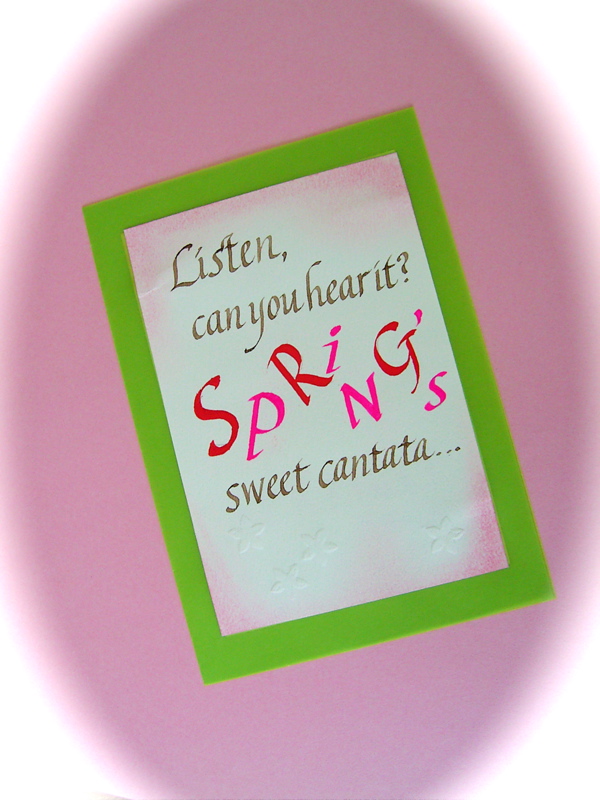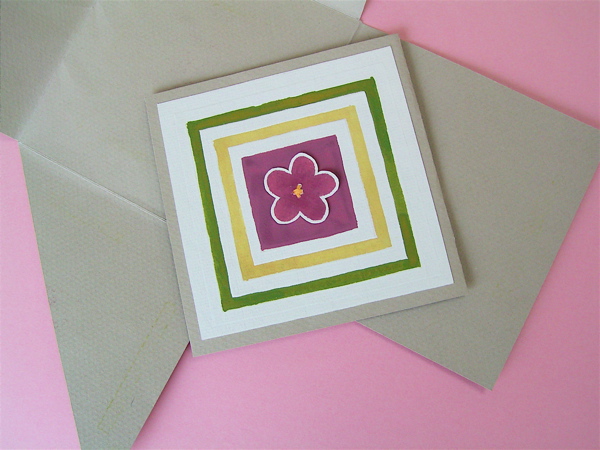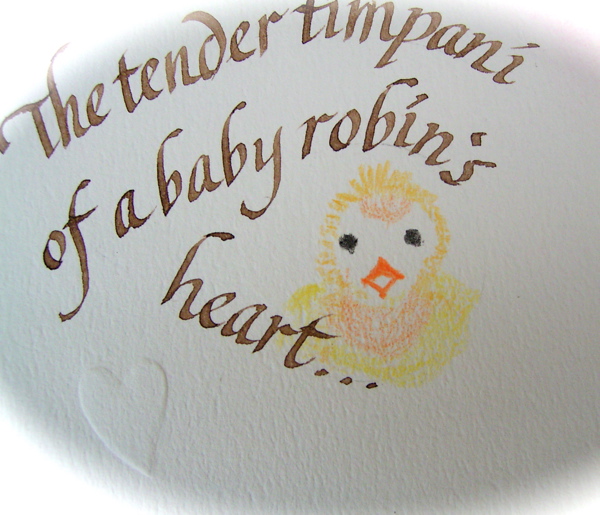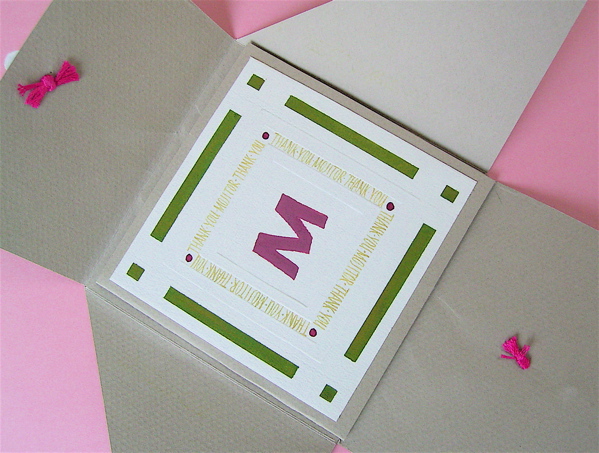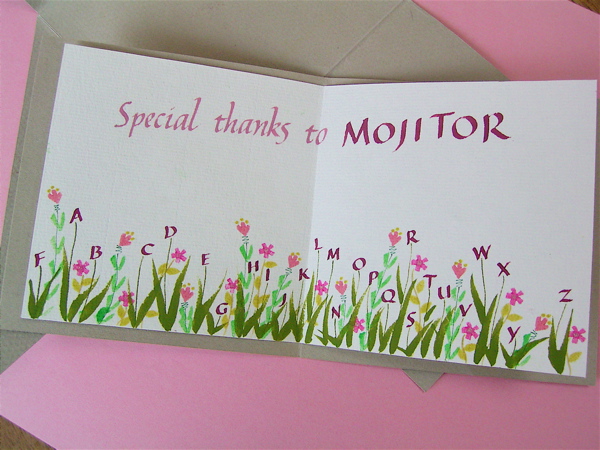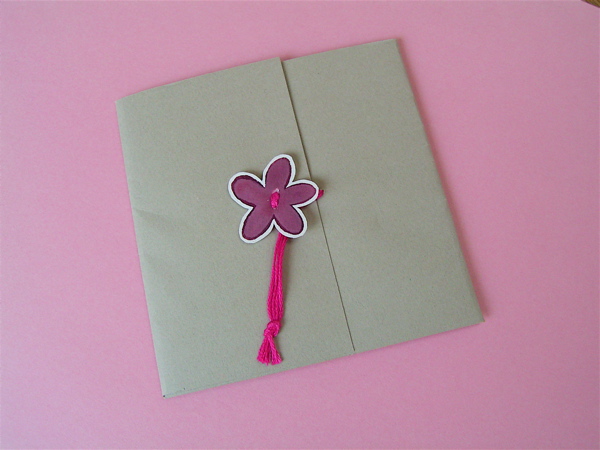
3月のエクスチェンジカード
3月のエクスチェンジカード、,最終回です!
春、春、春! プリマベーラ!
3月のカードとして春らしくやさしい二つのカードが届きました。
カワイイ〜!!
ウレシ〜!!
お花はよく見ると小さなスタンプを押してある様です。きっと作ったのでしょう!なんという手の込んだカードなのでしょう。本当に手作りの良さが表れている素晴らしいカードですね!
さてもう1点はKIさんからのカードです。こちらもWonderfulです!
パステル、エンボスを使った柔らかなイメージのカード。
きみどり色のクロマティコとピンクが春そのものの色で素敵です。
中を開いたら!
こちらは色鉛筆で描いてあります。もうやられた!と言う感じです。
あまりにも可愛いのでアップをどうぞ!
このカードの素敵なところは、紙や色の選択、きちんと書いた文字、エンボスやパステルなどのいろいろなテクニック、といろいろありますが、光っているのはこのとても素敵な文章です。
Listen, can you hear it?
Spring cantata....
The tender timpani of baby robin's heart......
D.Frolov
このひよこちゃんは、こまどりの赤ちゃんだったんですね〜